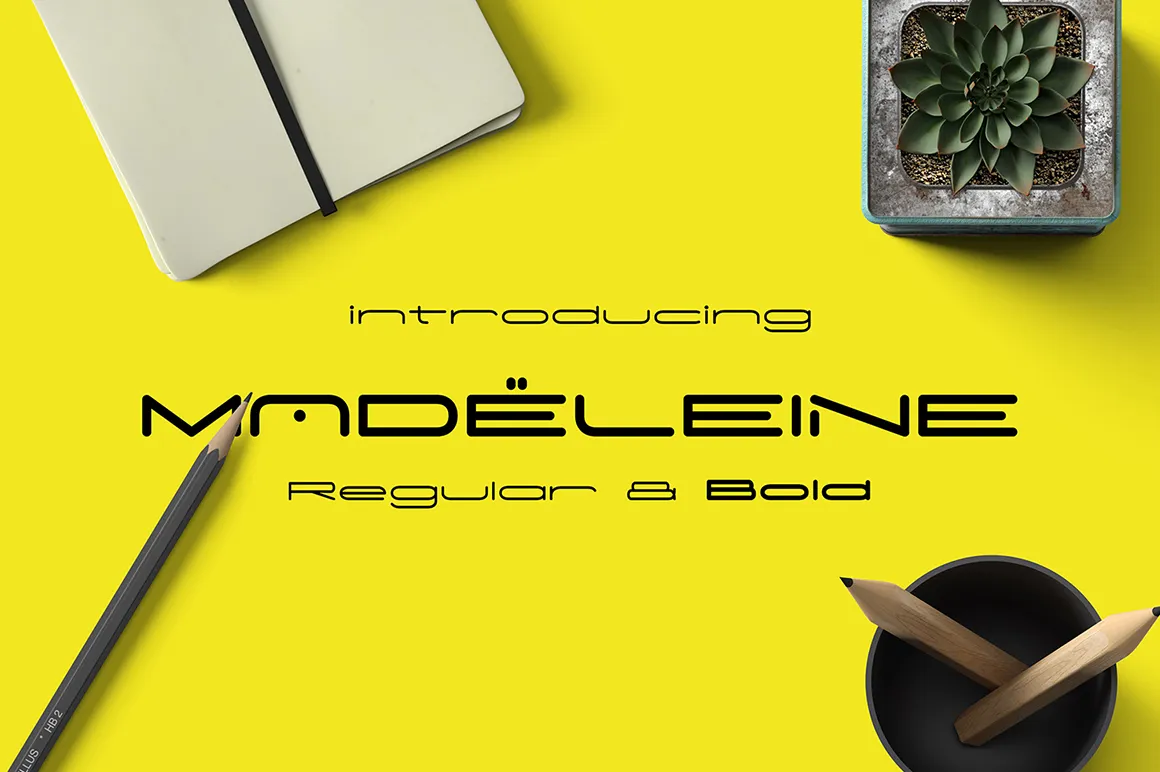
Bem-vindo ao mundo das fuentes digitais! Hoje, queremos apresentar a você uma novidade especial — Madeleine Font, uma famosa fã do tipo Sans Serif desenvolvido por nossa artista criativa e dedicada, madeDeduk. Com um design minimalista e moderno, Madeleine é perfeito para criar mensagens claramente legíveis e modernas. A fã tem seu próprio charme elegante, proporcionando uma paleta de opções interessantes que vão desde textos sociais até cabeçalhos de página em sua versão completa. Se você está procurando por mais fontes inspiradoras do madeDeduk, visite o nosso marketplace para explorar uma ampla variedade de outros recursos gráficos. É uma ótima maneira de adicionar ainda mais profundidade e personalização ao seu próximo projeto. Aqui está Madeleine Font, a sua nova paleta de cores para criar algo único e cheio de estilo!